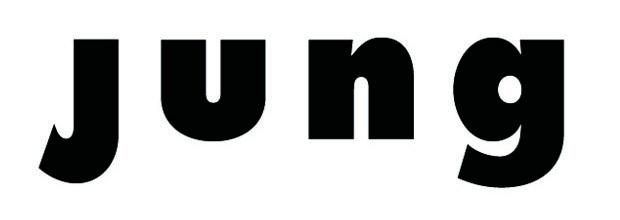
Wer kennt diese zwei Schriften und kann mir weiterhelfen? ..
1) "Projekt Consult" - achtet mal bitte besonders auf das "C", auch auf das "S" und das "R"
das ist keine Futura oder Univers:
2) Wer oder was könnte das sein? Ist ein Logo und sieht nach Futura Extrabold aus:
... Futura Extrabold mit nochmals gestauchtem und versetztem "Versal-J".
Welche Schrift könnte jetzt noch in der Line: "Projekt Consult" stecken?
Wenn das so wäre, hätte ich wohl schlechte Karten, denn diese Ersatzfonts
funktionieren ja unter Mac OS X nicht mehr. Fällt euch da eine Alternative ein?